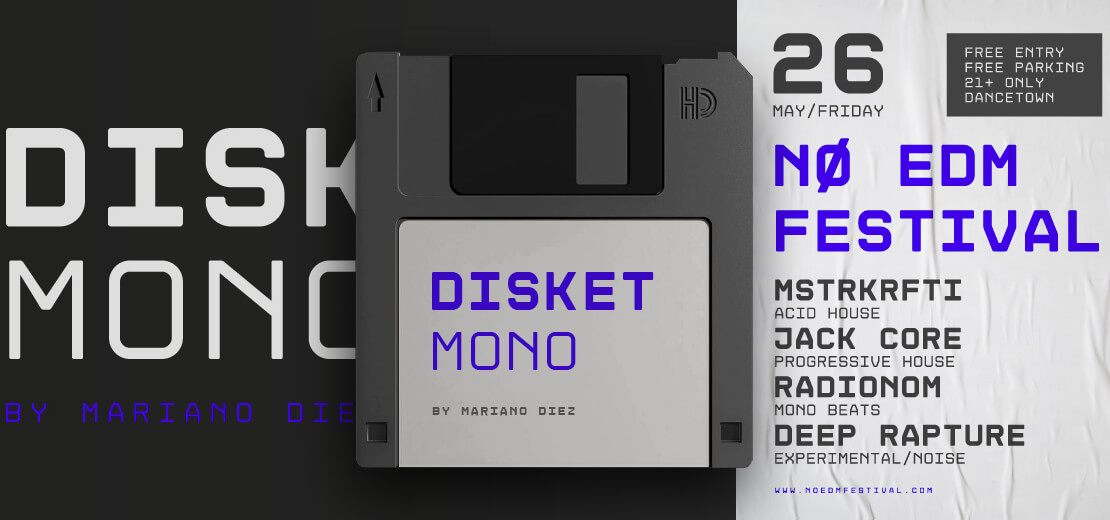
Disket Mono
Disket Mono ist eine Monospaced-Schriftart, die von ihrer Gestaltung her an die guten alten Disketten erinnert. Die Free Fonts gibt es in zwei Schnitten zum Downloaden.
Disket Mono
Mariano Diez hat sich außerdem von Geometrie, Rastern und Architektur inspirieren lassen. Unterstützt werden 20 Sprachen. Das kyrillische Set stammt von Denis Ignatov.